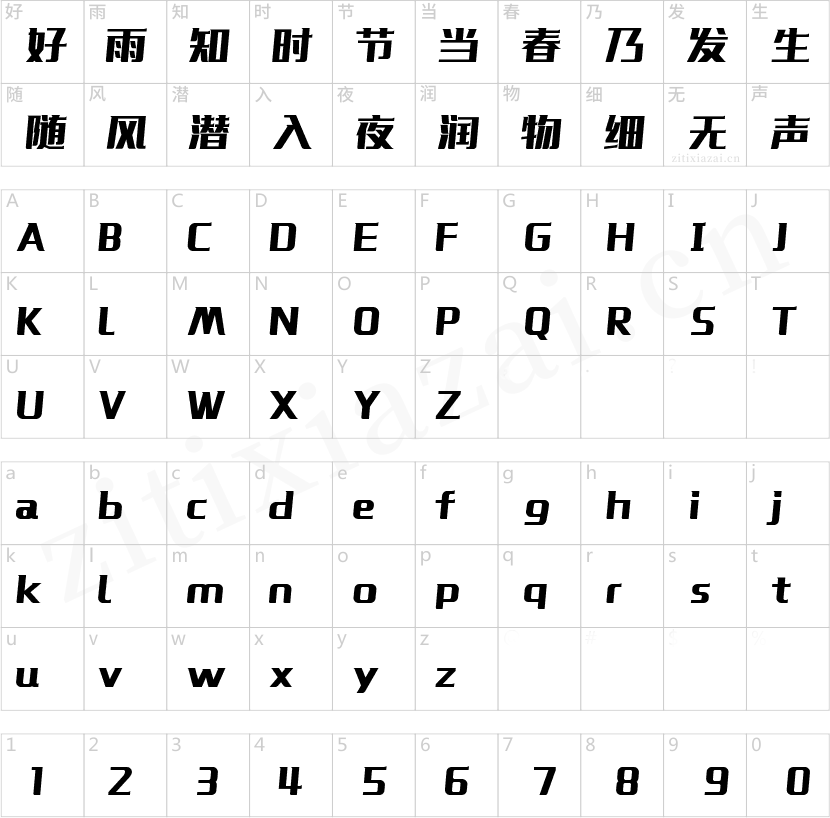
壹心冲锋号
壹心冲锋号,这款字体结构工整、笔画清晰,兼顾美观与易读性,适用于标题、正文、海报、包装、LOGO 等多种场景。字形优雅稳定,风格百搭耐看,适配日常排版与创意设计,让文字呈现更舒适、更具质感。壹心冲锋号一笔一画,皆是细节,以均衡的比例、流畅的线条打造舒适视觉体验,字形端正大气,风格简约现代。无论是商业设计、品牌宣传还是日常排版,都能轻松驾驭,让文字更有格调与力量。壹心冲锋号字体下载。